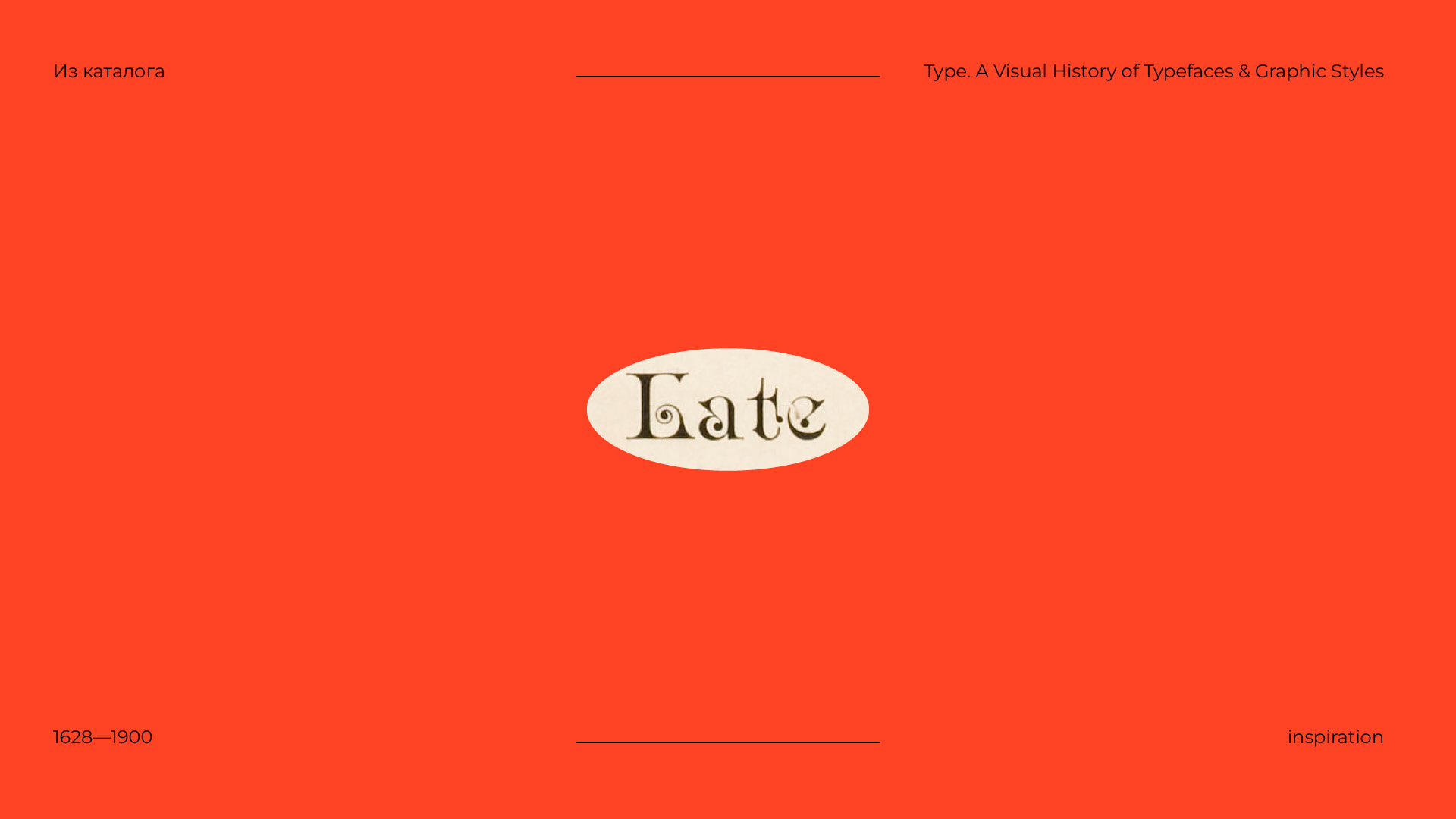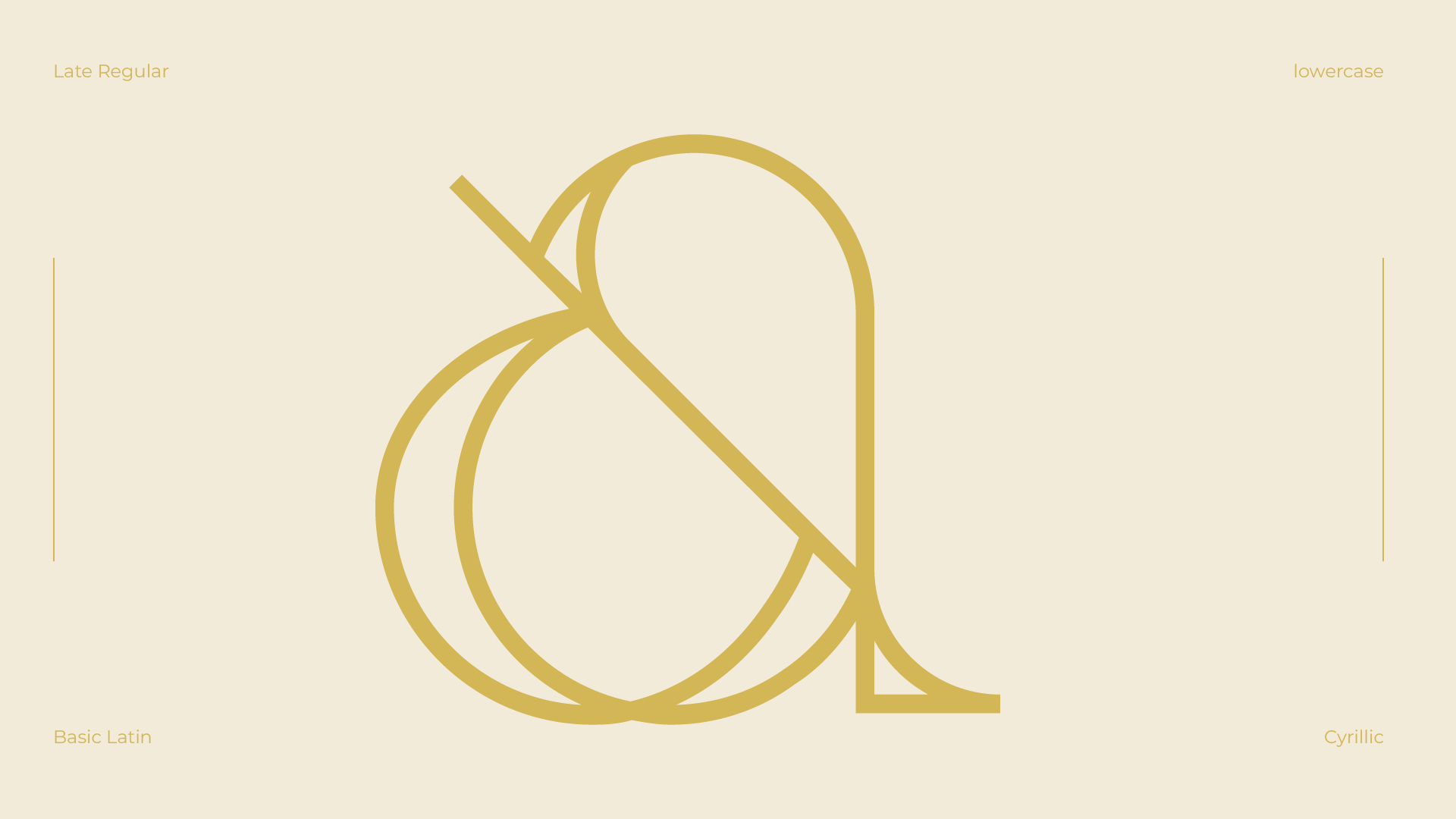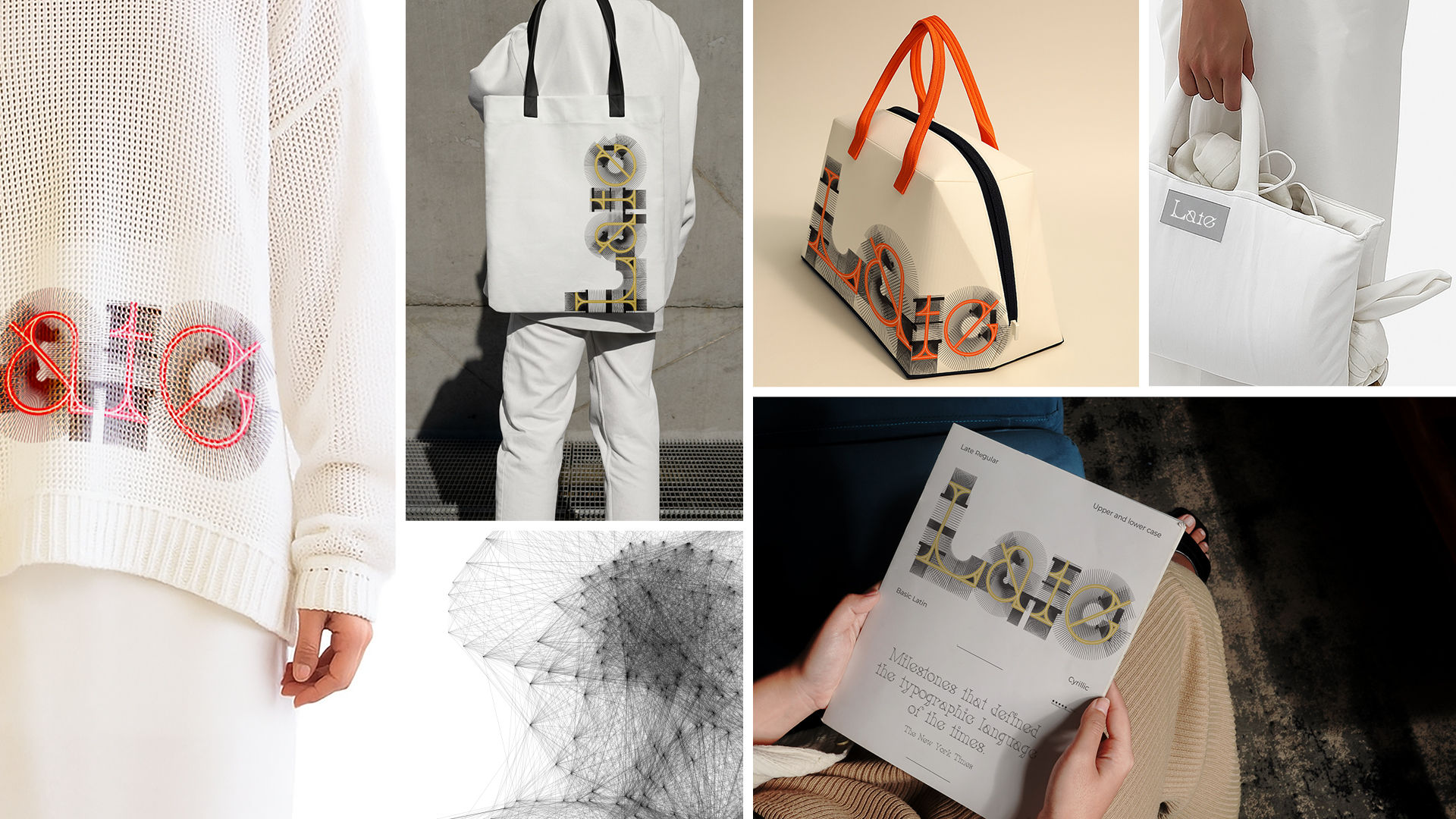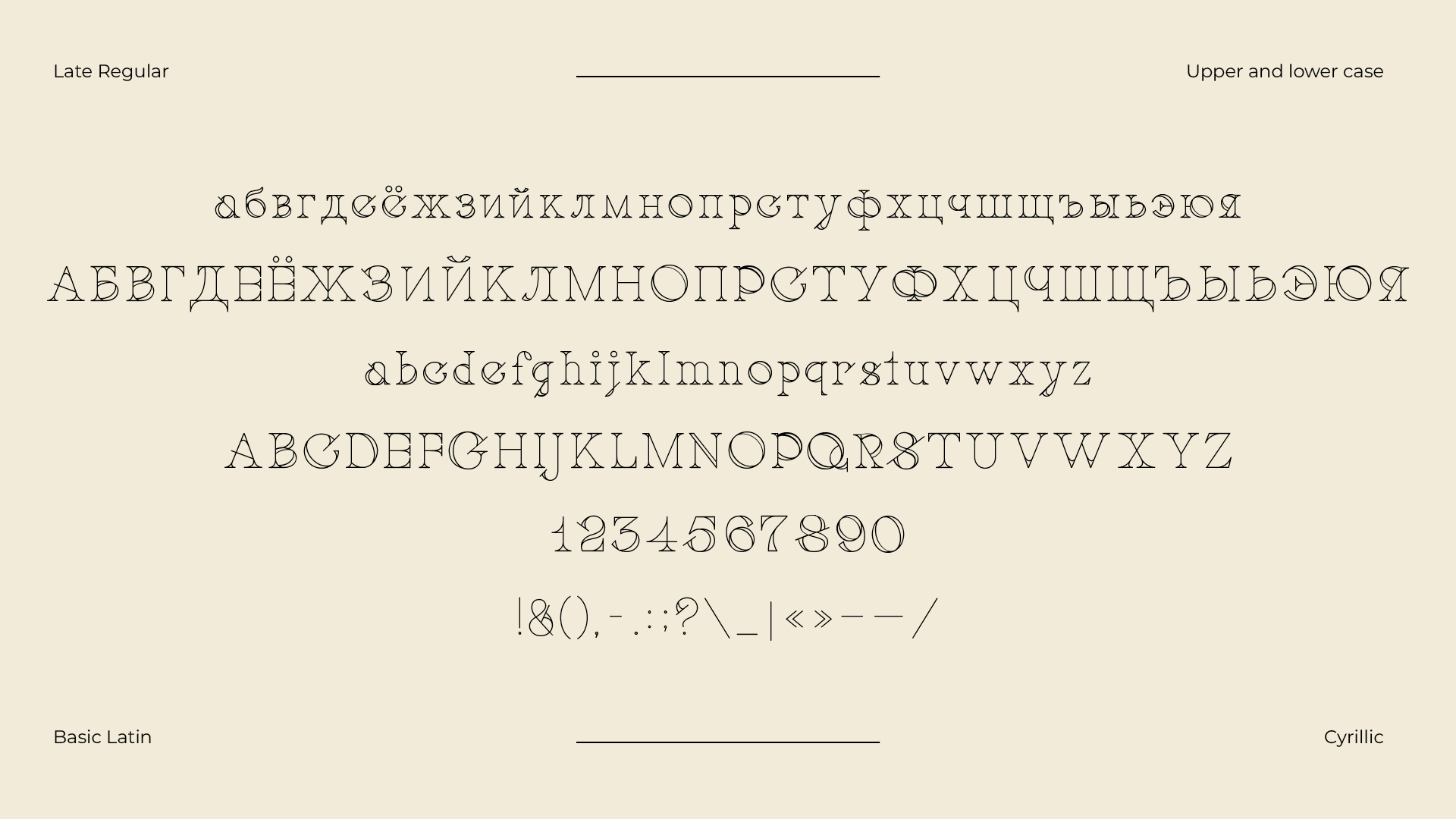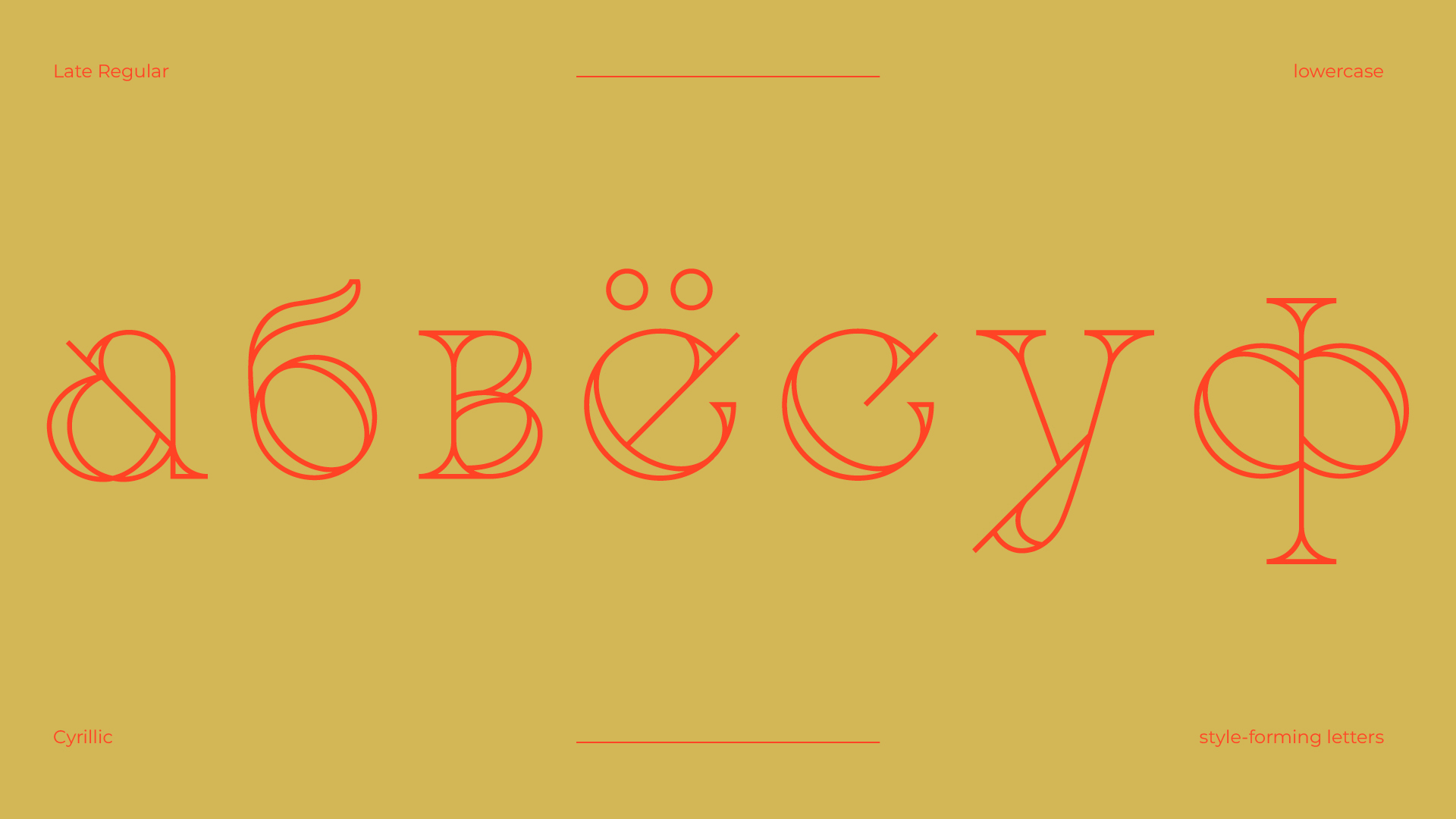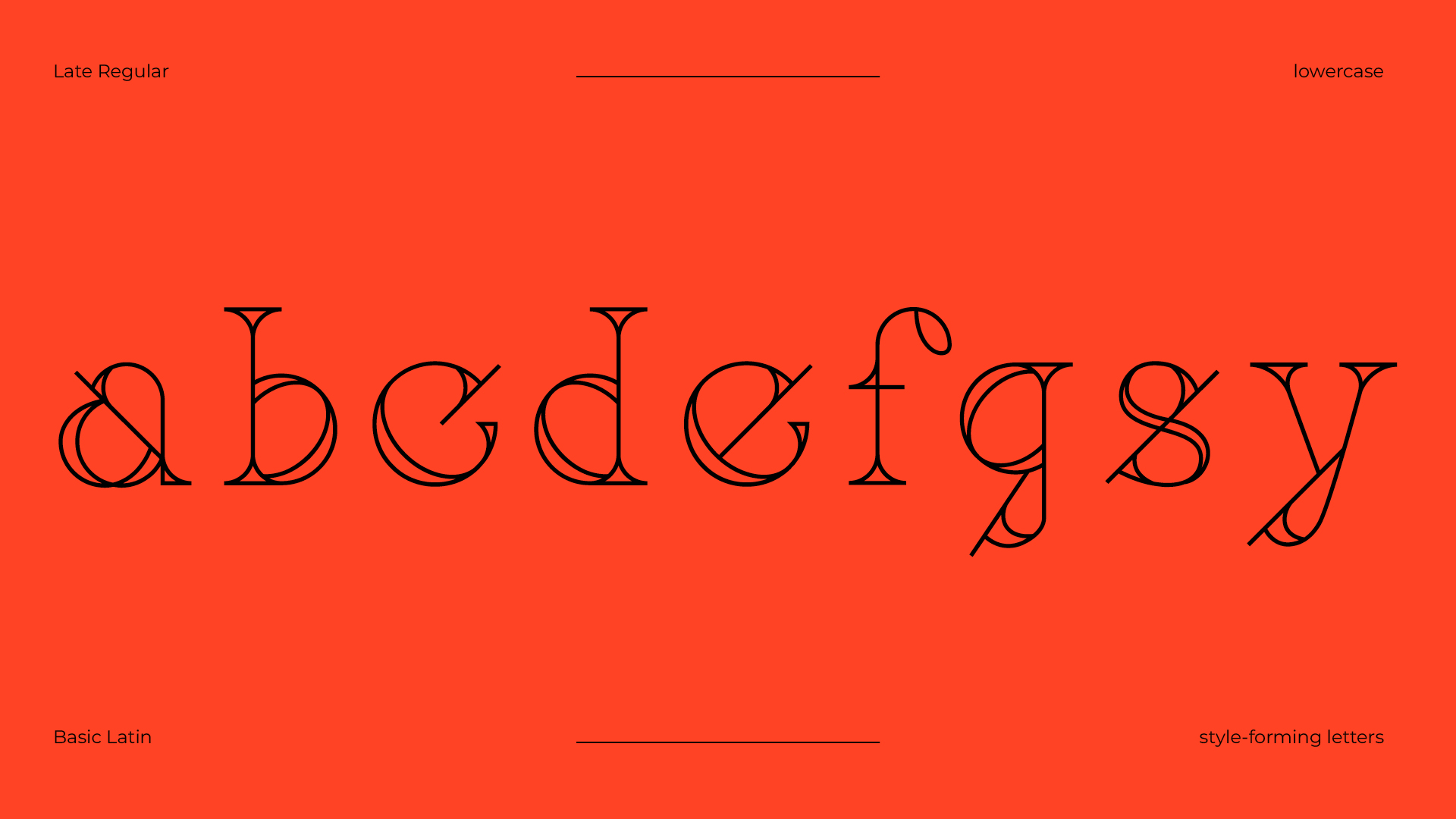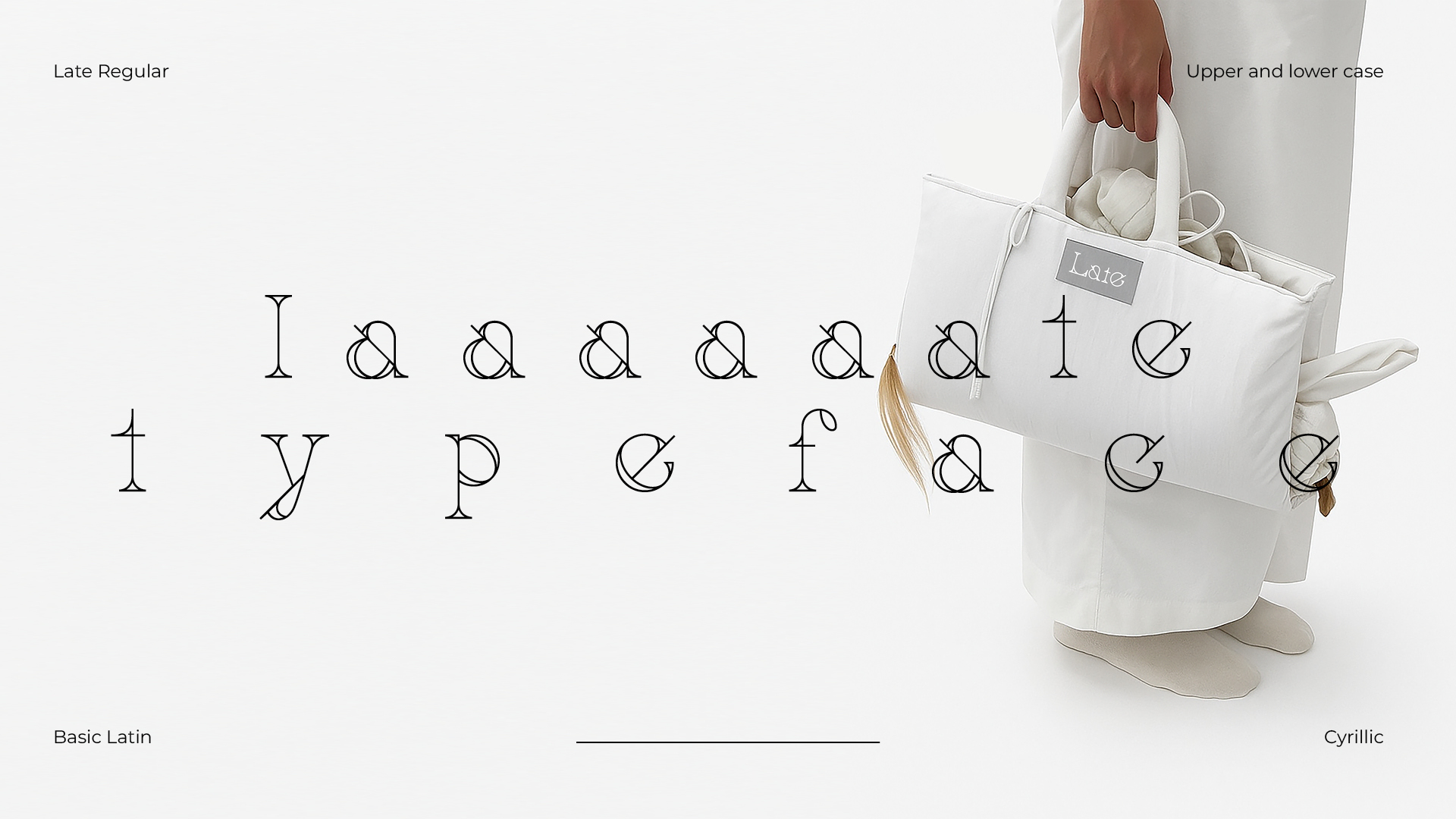
Late
Шрифт Late — чистое вдохновение от увиденного однажды необычного шрифтового решения в книге издательства TASCHEN "Type. A Visual History of Typefaces & Graphic Styles". На мой взгляд, шрифт Late приобрёл кросс-культурный характер, что делает его актуальным для различных визуальных коммуникаций. Стиль обращается к широкой аудитории, что позволит ему находить отклик независимо от визуального языка или сферы применения. Гармоничное сочетание традиций (увиденный кусочек из книги TASCHEN) и современности в образах новых букв, а также широкие возможности применения делают его чрезвычайно привлекательным для работы с типографикой. Каждый шрифт — это не просто набор букв, это история, эмоция и источник вдохновения. Надеюсь, мой новый шрифт Late станет для кого-то вдохновением.